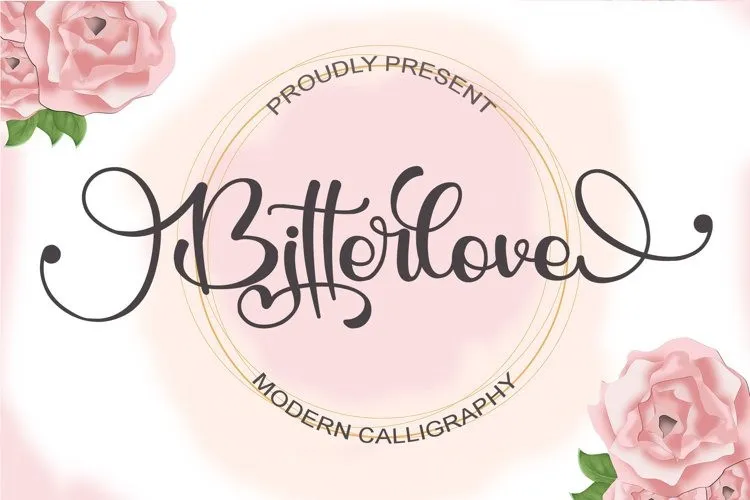
Bitterlove Font – Download Grátis
A Bitterlove Font é uma opção irresistível para designers que procuram uma paleta de caracteres únicos e fofos. Ela surge diretamente do talento da Letterafa Studio, oferecendo letras fluidas que adicionam um toque único aos seus projetos digitais. Esta fonte é perfeita para uma variedade de aplicações, desde logotipos até cartões de agradecimento e embalagens customizadas, passando por design de arte útil (DIY), títulos de livros, convites de casamento, embalagens e muito mais. Sua personalidade suave e divertida se destaca em qualquer projeto que ela seja aplicada, tornando-a um recurso indispensável para quem busca uma fonte que traga diversão e originalidade à sua obra.